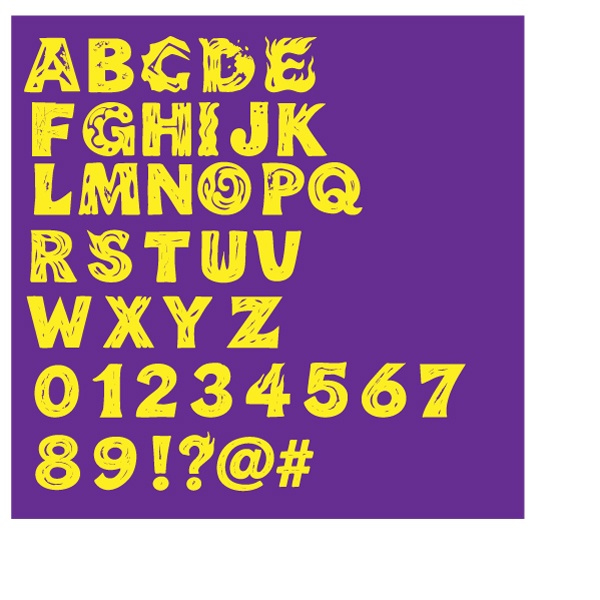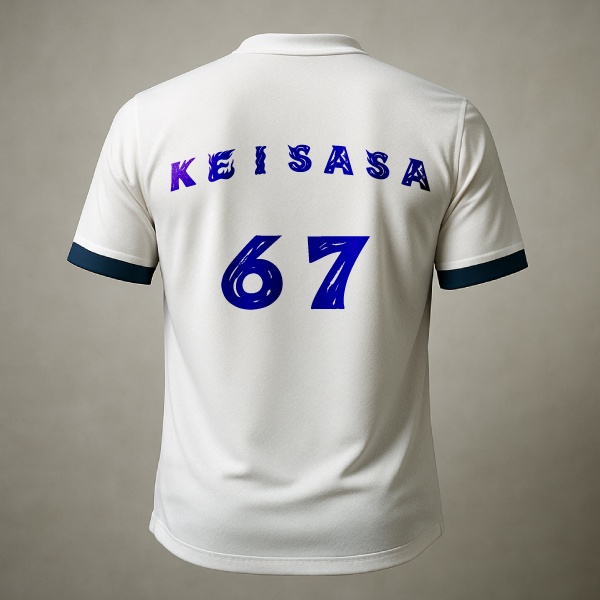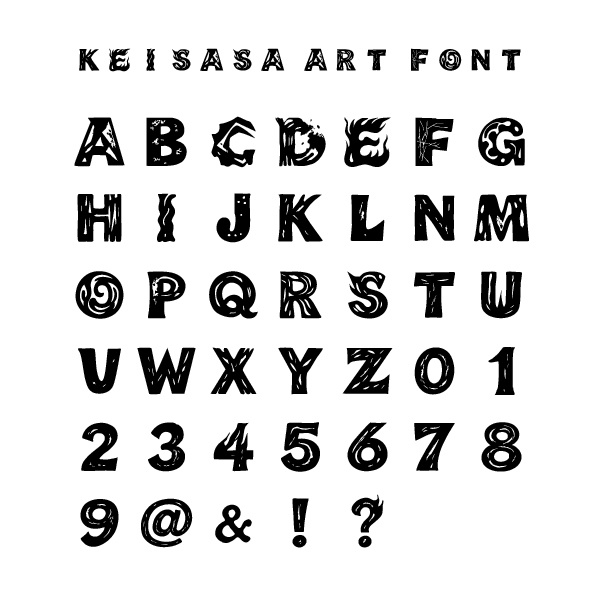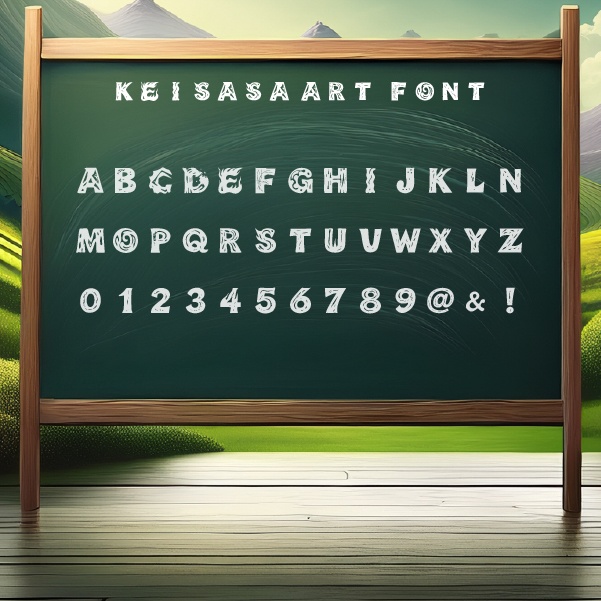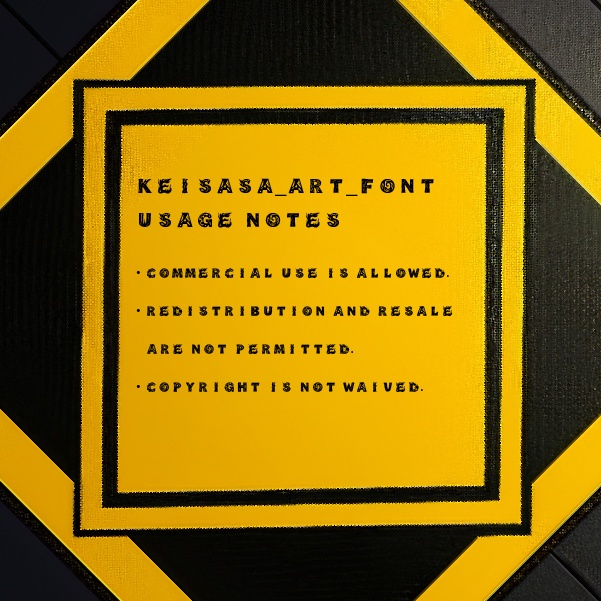
【商用可】Keisasa art font.ttf|アート系グルーヴィフォント
🌀 Keisasa Art Font あなたの作品に“怪しさ”と“個性”を添えるアートフォント、ついに登場! 🖋 商品概要(スペック) フォント形式:TrueType(.ttf) 収録文字:A~Z(大文字英字)、0~9、記号一部(!?@&) 対応OS:Windows / macOS 🎨 制作の道のり このフォントは、グラフィックデザイナー「ササキ」が一文字ずつIllustratorで手描きし、まるで「彫刻を彫るように」創り上げたものです。奇抜でアート性の高いフォントが欲しいという思いから、試行錯誤を繰り返し完成しました。 普段のフォント制作では使わない「手癖」「ノイズ」「偶然性」をあえて活かし、唯一無二の“うねり”を表現。見る人に強烈な印象を残します。 💡 こんな人におすすめ 他とは違うインパクト重視のフォントを探している方 アートZINE、CDジャケット、展示告知、MVサムネなどを制作している方 「個人制作でもちゃんと目立ちたい」と思っている方 ✅ 利用について 商用利用OK(クレジット不要) 再配布・転売は禁止 改変しての使用(アウトライン化など)は自由 フォント自体の著作権は放棄していません 🎉「Keisasa Art Font」で、“クセが強い”作品づくりを始めよう! This is an original TTF font designed by Japanese artist Keisasa. Available for commercial use. Ideal for creative design, games, and more.